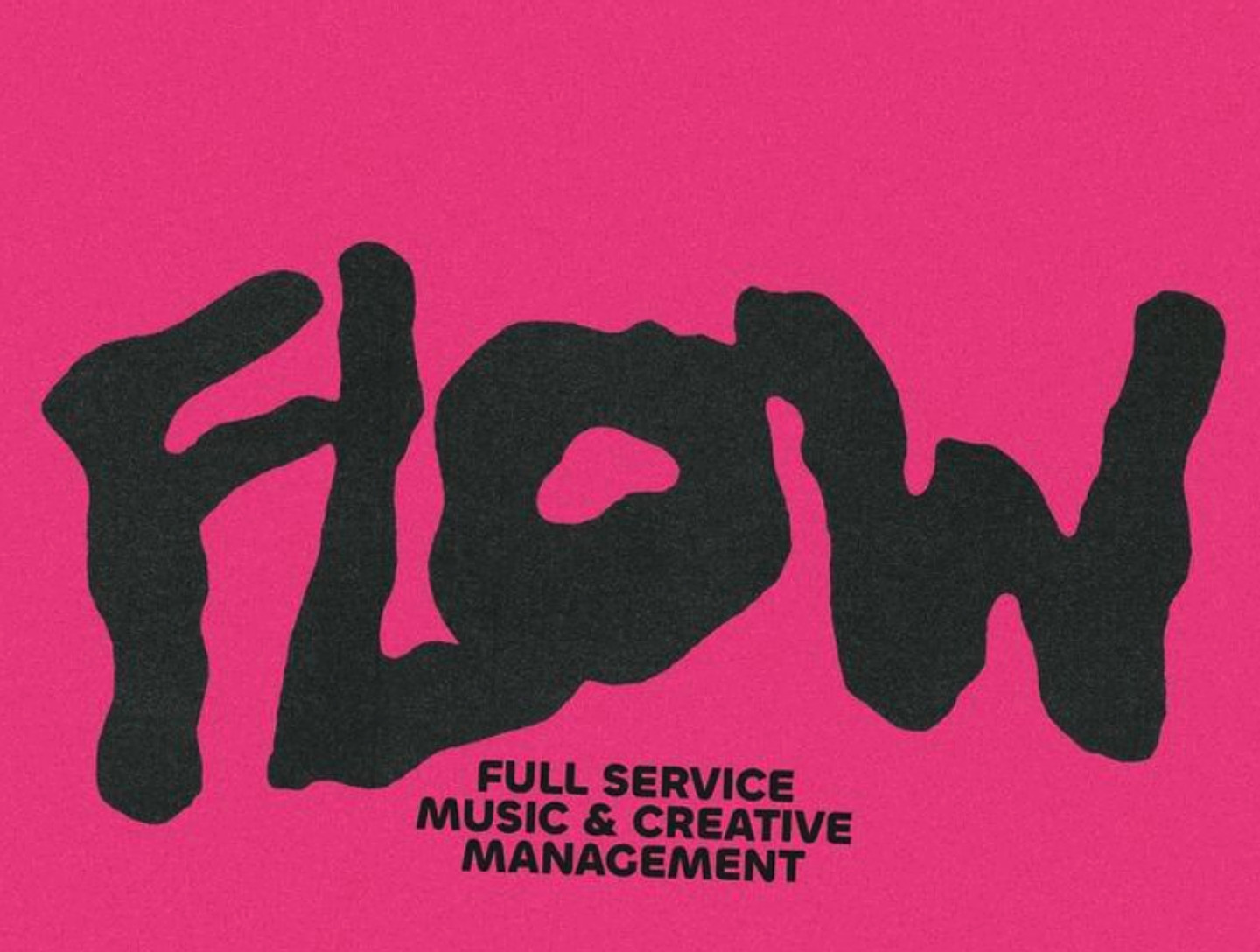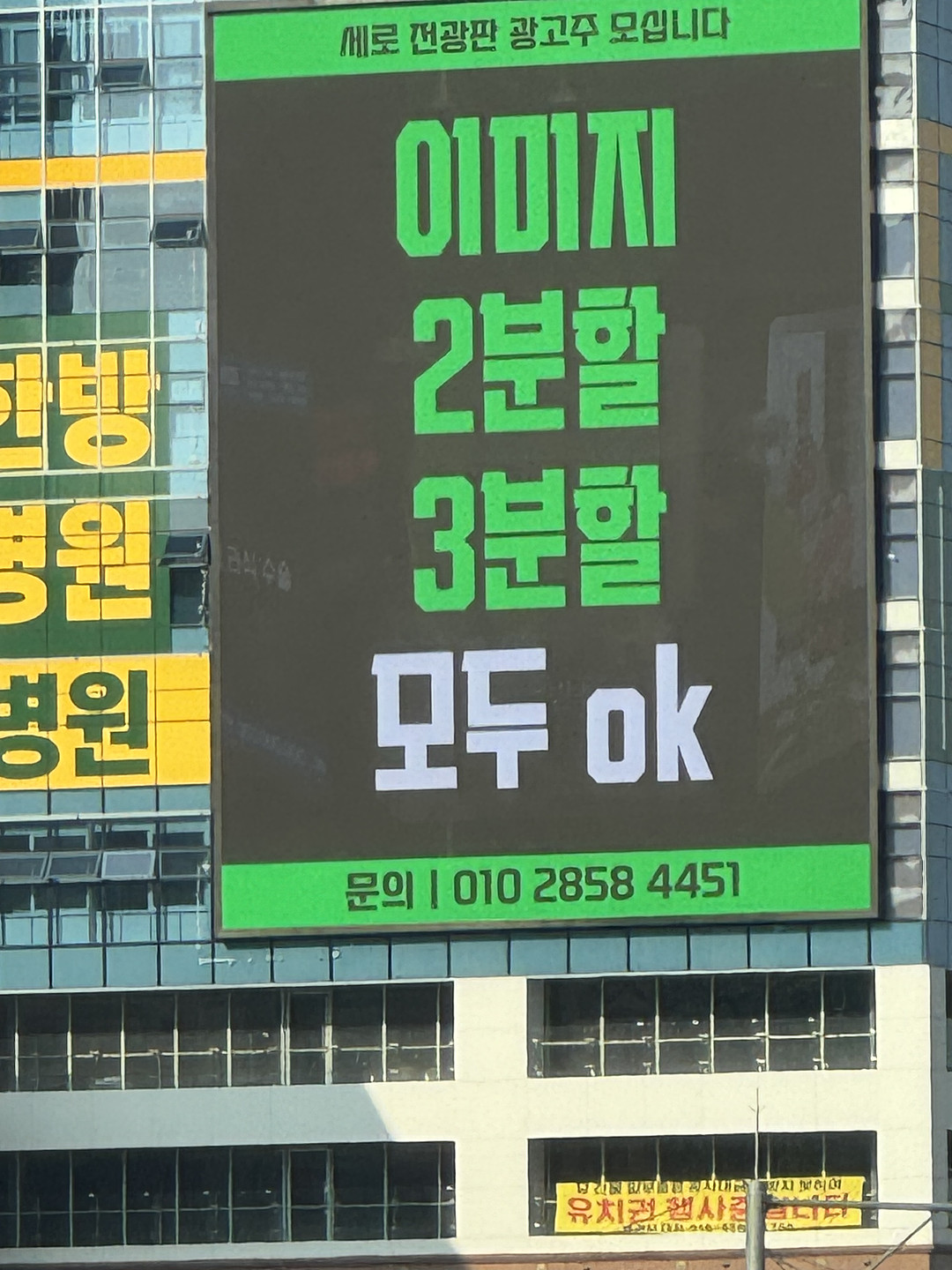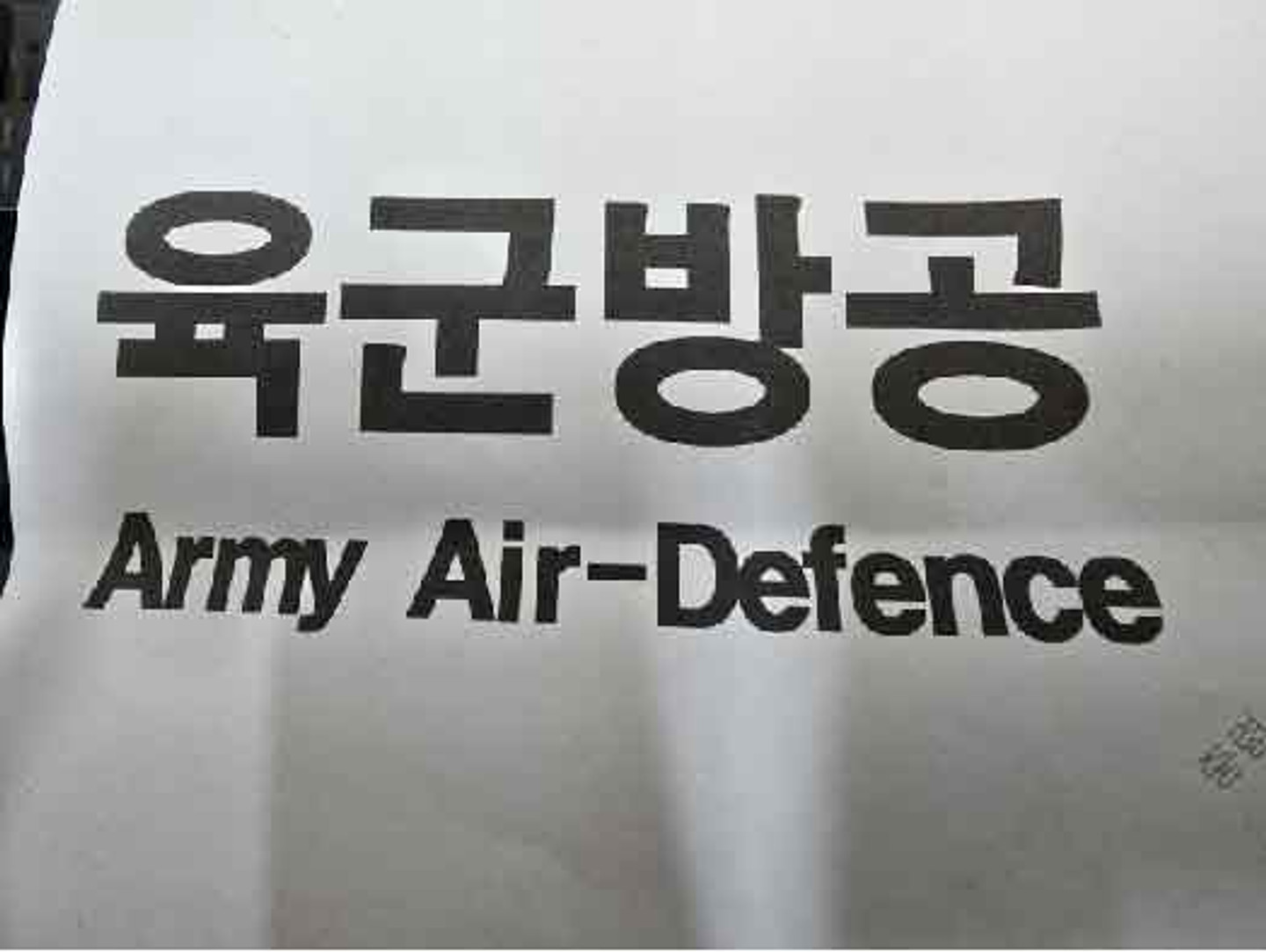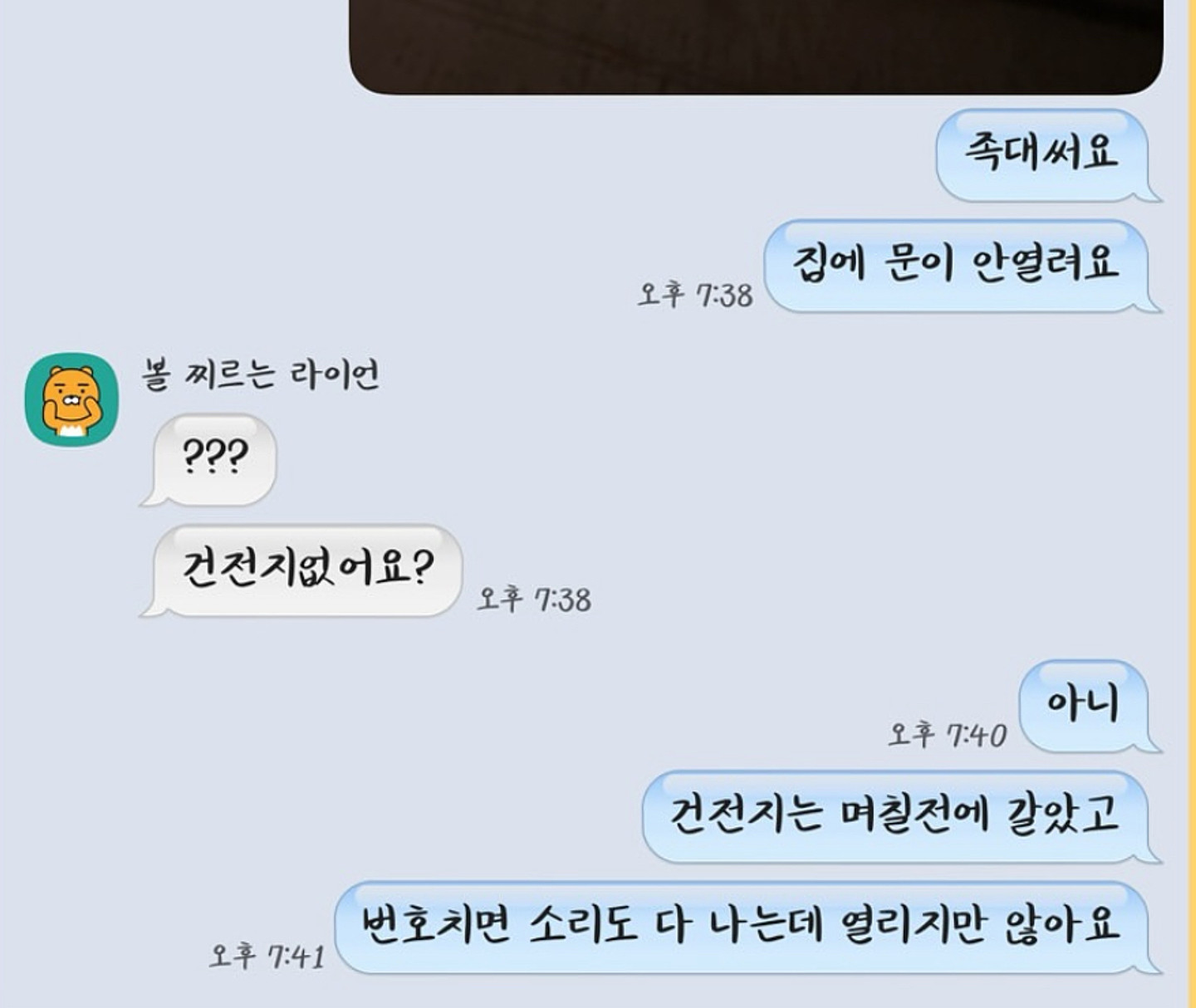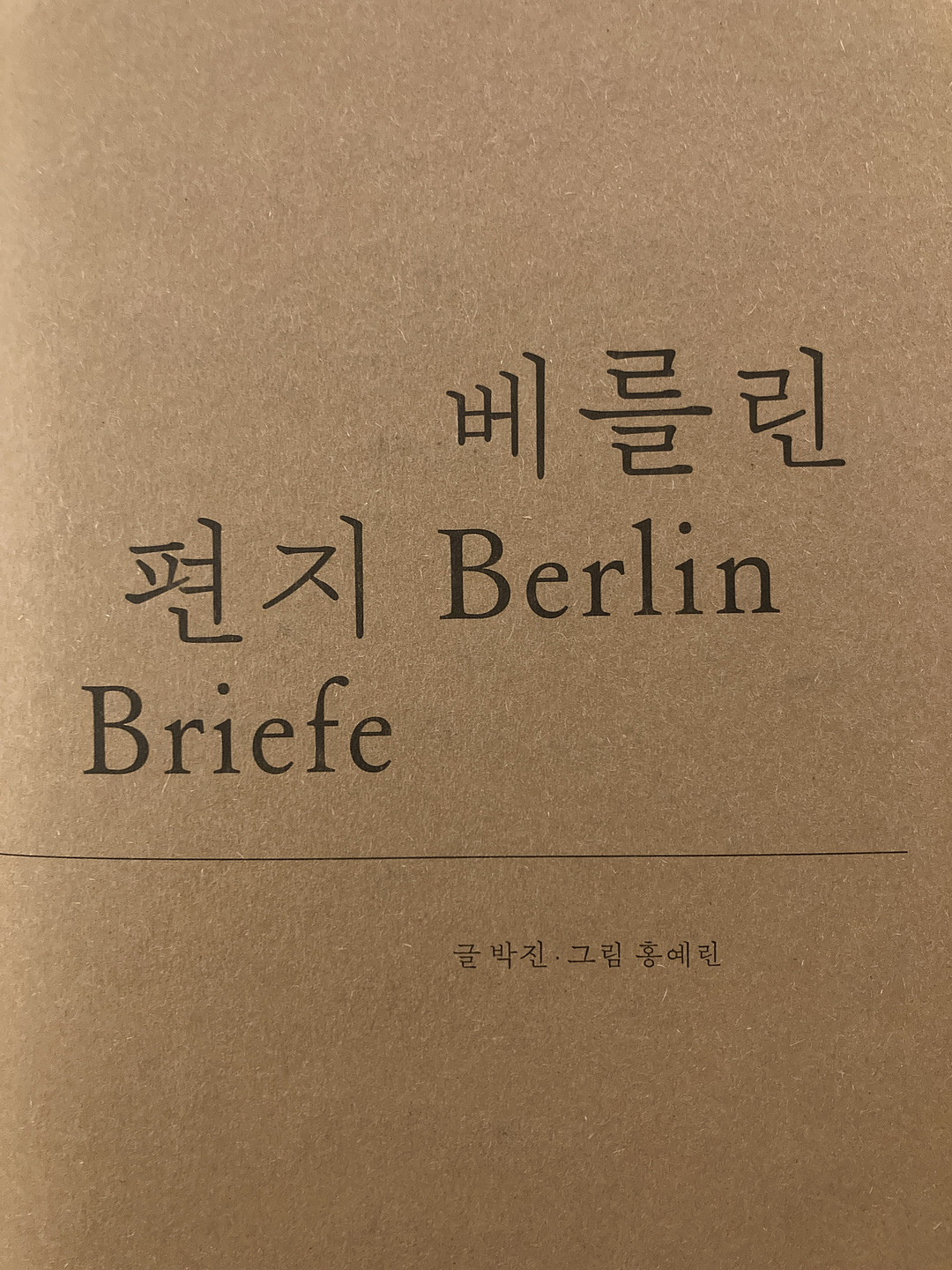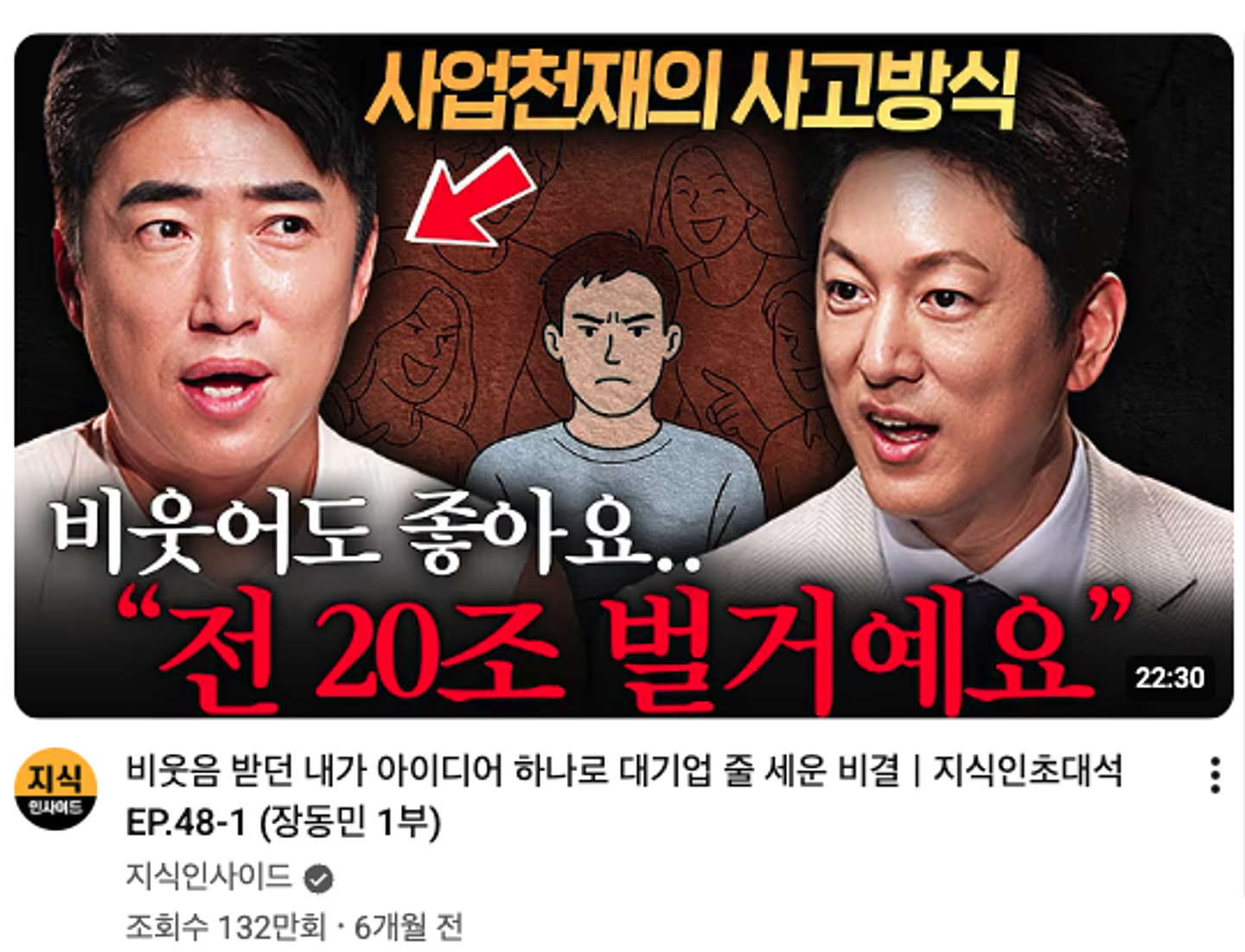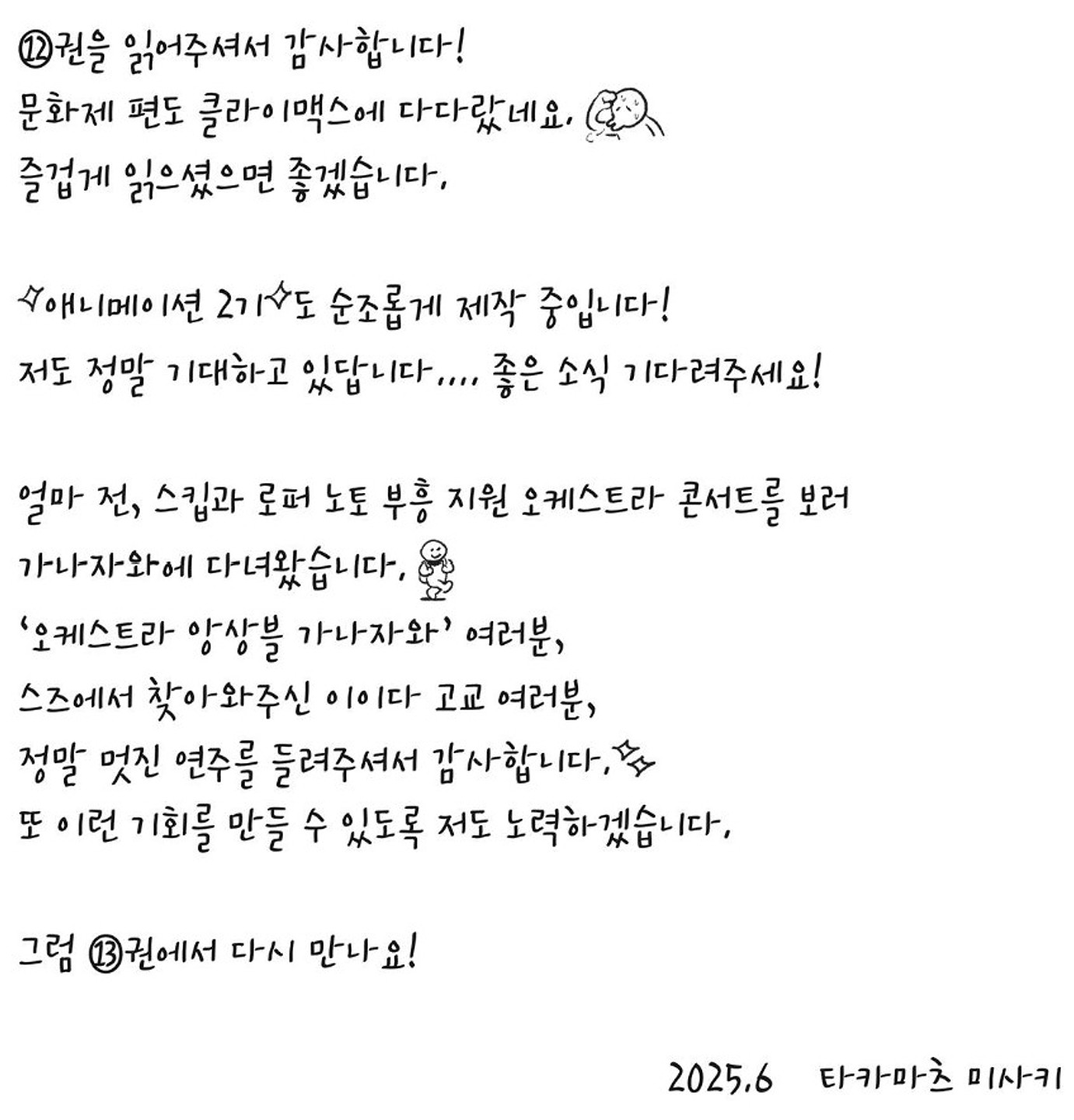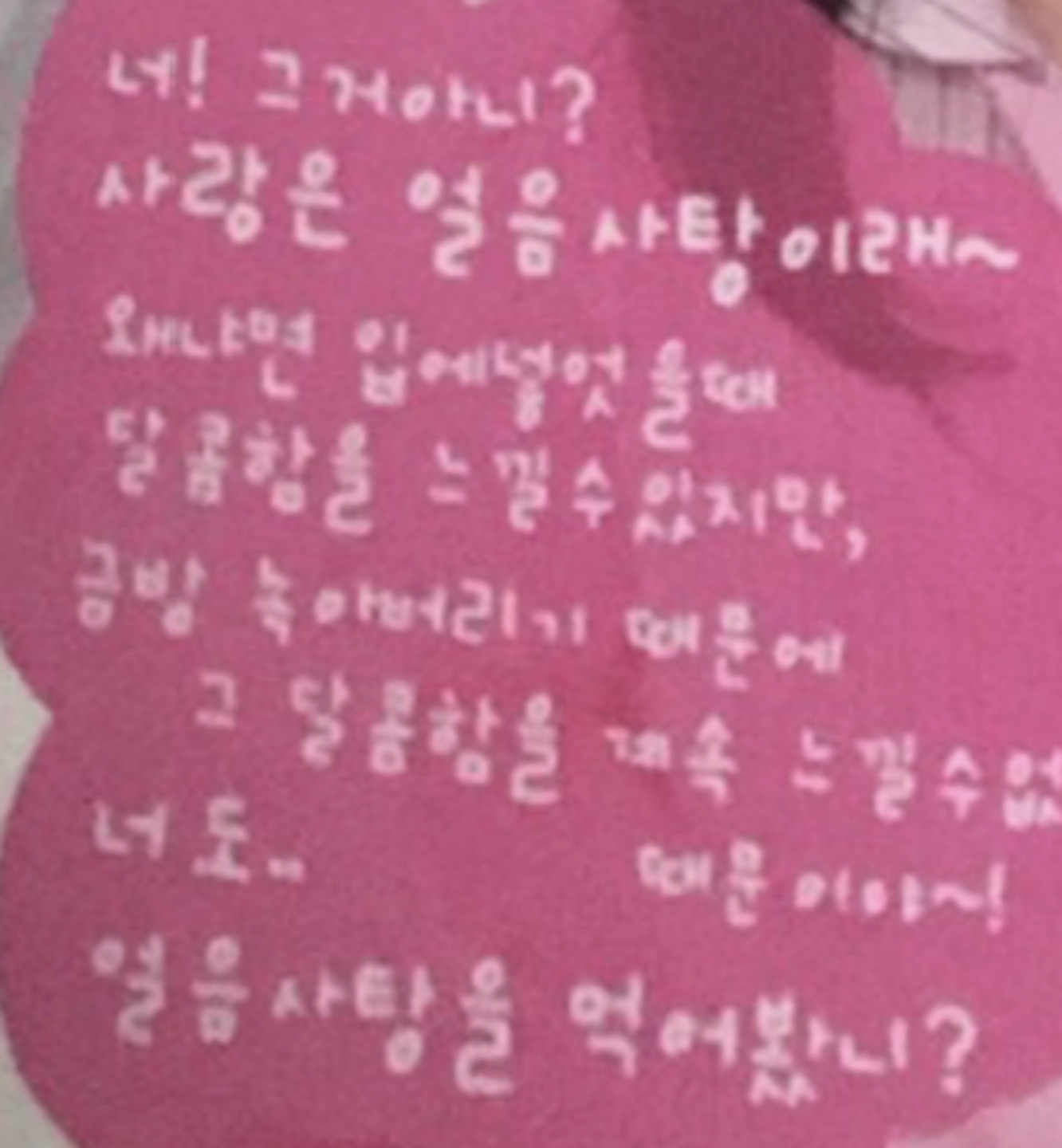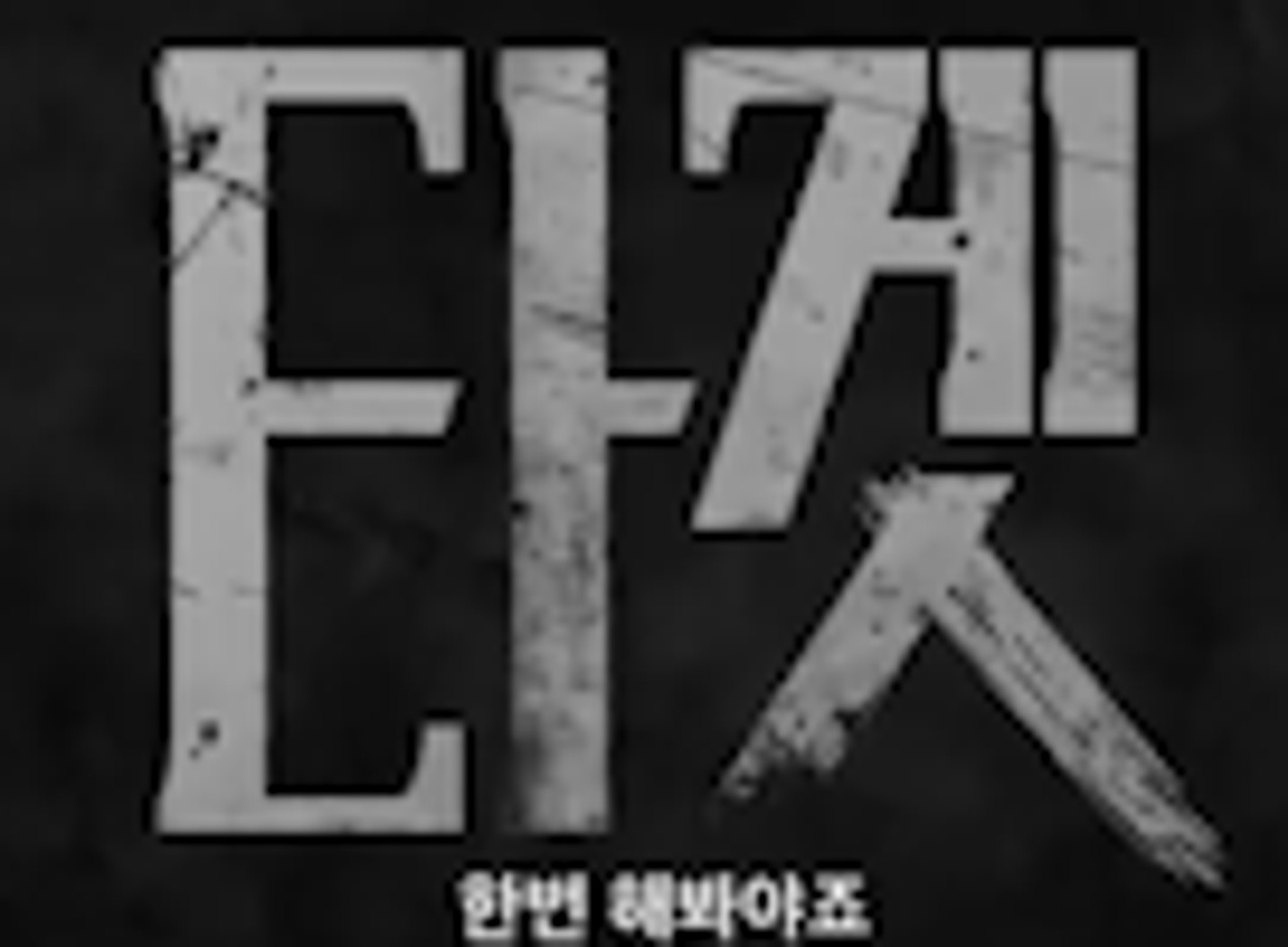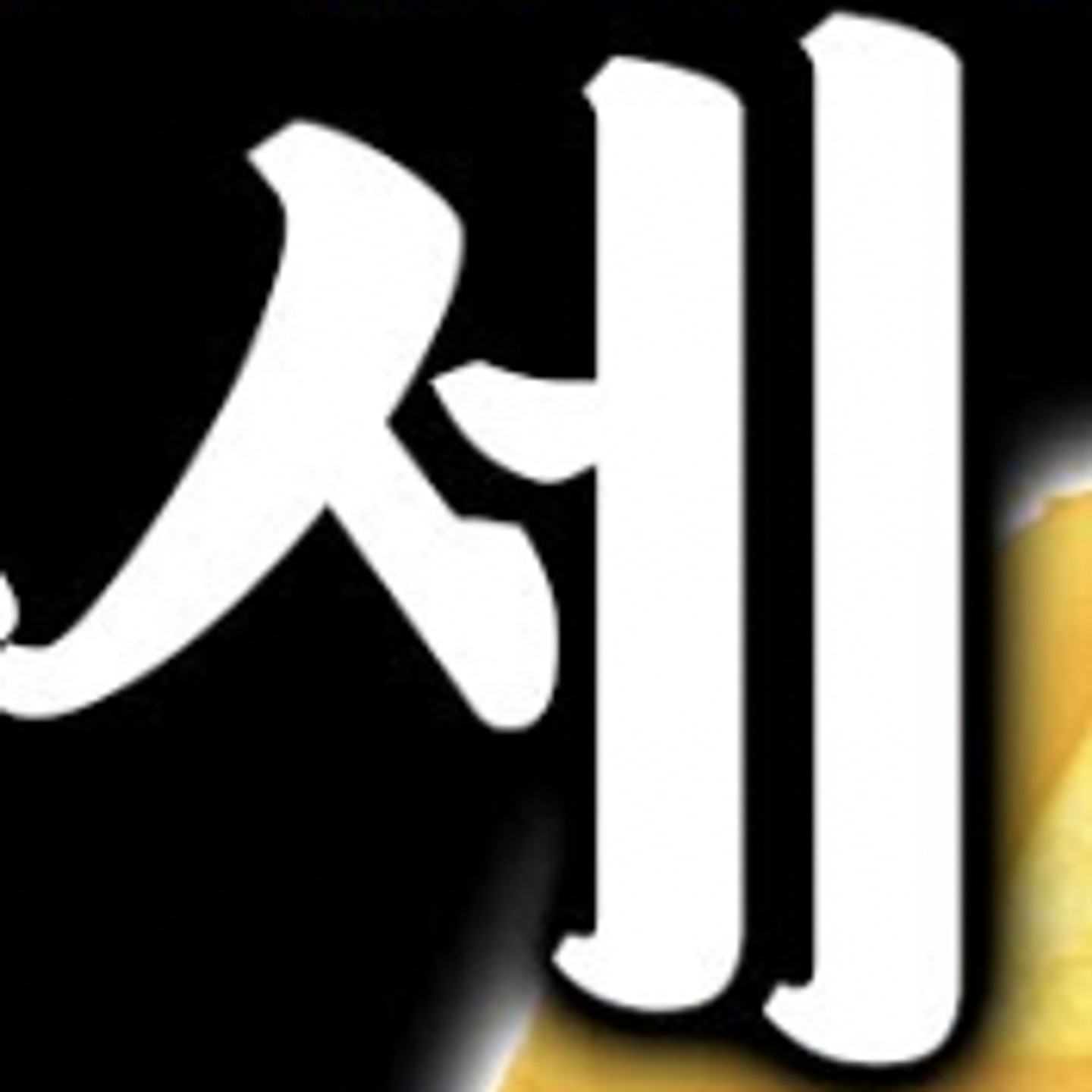
인스타 광고인데 이 글씨체 알려주세요 !! 엉엉 ㅠㅠ
이거 무슨 폰트일까요??
뭔가염
이 폰트 아시는 분 계신가요??ㅠ
흰색 자막 위에 있는 귀여운 자막이 뭘까요?ㅠㅠㅜㅜ
등번호 폰트인데 알수 있을까요
무엇인가요
영문 폰트 무엇일까요?
2026년 9월 공개된 쥬베룩(JUVELOOK)의 광고 캠페인 슬로건 입니다 이 서체에 대해 알 수 있을까요?
작업치료사협회 홍보물인데 어떤 폰트인가요?
카카오톡 글씨체로 쓰던건데 삭제하고 다시 깔았더니 폰트를 잃어버렸어요.. 시스템에 깔려있는 폰트도 없고 카카오톡에서 기본으로 제공하는 폰트 목록에도 없는 것 같더라고요 제발 무슨 폰트인지 찾아주세요… ㅅ 부분이 포인트인 것 같아요 그리고 손글씨체 같아 보이지만 고딕굴림? 쪽에 더 가까운 것 같기도 해요
이 폰트 정보 알고 싶어요!
캡컷에 있을것 같은디ㅠㅠ
비슷한 폰트라도 알려주실수 있으신가요? 인천군 숫자 마킹 폰트입니다
이폰트알려주시면 감사하겠습니다! 빠른 채택 해드릴게요!!
이 폰트 알려주시면 감사하겠습니다!! 빠른 채택 해드릴게요!!
무슨 폰트인지 궁금해요.
이 폰트가 뭔지 알려주세요~
MOODBOARD와 MONDAY 폰트 알려주세요
이 폰트가 뭔지 알려주세요!
무슨폰트인지 아시느분 답변 부탁드립니다
해당 폰트 혹시 아시는 분 계실까요?
이 폰트 알려주세요ㅜㅜ
폰트 궁금합니다! 알려주시면 감사하겠습니다~
파노라마 위에 영어 폰트 알려주실분 ... ㅠ 요즘 필기체 같은데 넘 이뻐요 ㅠ ㅠ
이거 뭘까요,,!!!
첫번째 글씨 어떤 폰트인지 알 수 있을까요?
이건 무슨 폰트인가요?
무슨 폰트인지 알려주시면 감사하겠습니다!!
혹시 이 폰트 아시는분 계실까요??
영어랑 한글폰트 뭔지알수있을까요? ai들은 인식을 못하네요 ㅠㅠ
저 폰트 뭨가요? 알려주시면 감사합니다
어떤 폰트인지 궁금합니다!
전남대학교병원 로고에 사용된 글자체 어떤걸까용 ㅇㅅㅇ
이거 무슨 폰트인지 아시는분?
엠스플 야구 중계에 잇는건데 혹시 뭘까용
이거 폰트 이름 뭔가욤...? 지금은 단종됐나요?
굴림체느낌인데 무슨폰트일까요
저처럼 본인의 강점은 어쩌고 적힌 저 폰트 뭔가요?? 묘은 흘림체인줄 알앗는데 다르네요 ㅜㅜ 미리감사합미다고수릠덜..
무슨 폰트예요?
무슨 폰트 인가요?!
이거 무슨 폰트에여?
"나를 움직이는 탐색" 무슨 폰트일까요?ㅠㅠ 급해요..
이거 어디서 봤는데 ㅠㅠㅠㅠ아시는분??
이 폰트 찾아주세요 ㅠ.ㅠ
이 폰트 알 수 있을까요?
우신영 작가의 소설 ‘블랙푸들‘의 메인 타이포가 궁금합니다! 블랙 푸들 블랙푸들 우신영
안녕하세요 폰트 너무 궁금해요
비포 에프터 폰트는 알았는데 & 폰트는 어떤 거 일까요 ㅜㅜ? 그리고 하단에 Eve Titan 폰트도 궁금합니다
폰트 이름 좀 알려주세요 ㅠ ㅠ
이 폰트가 어떤 폰트인지 알 수 있을까요? 비슷한 거라도 아시면 알려주세요ㅠㅠ
비슷한 폰트를 찾고 싶어요
무슨 폰트일까용 ㅜㅜ 무료로 추천도 부탁드립니다 !!
이런 느낌의 장식체가 정보가 필요합니다..!! 영문 폰트면 더 좋고 비슷한 폰트 종류 다 괜찮습니다!!